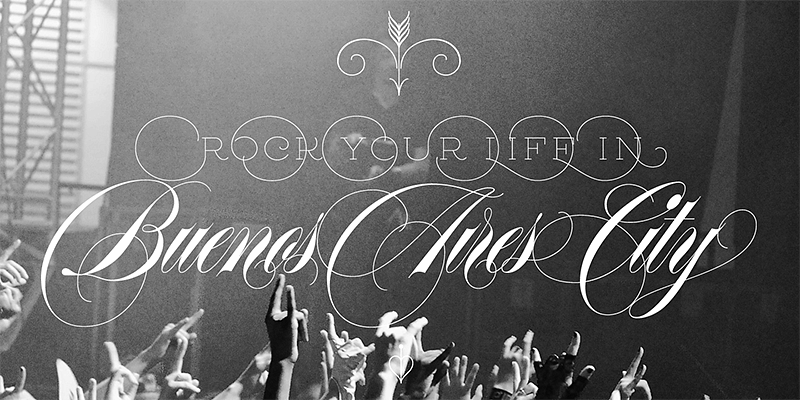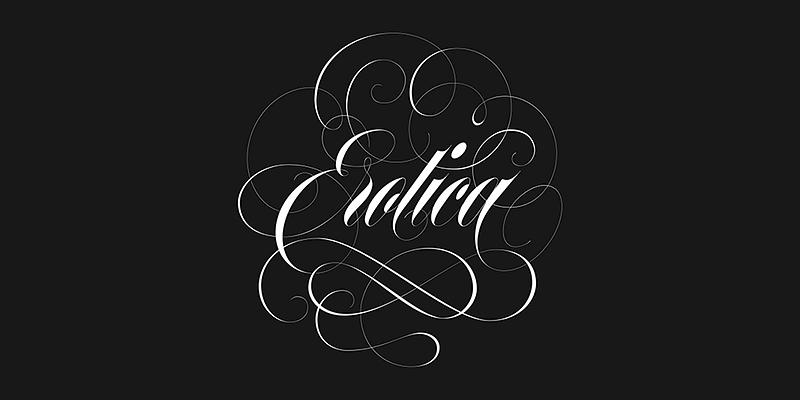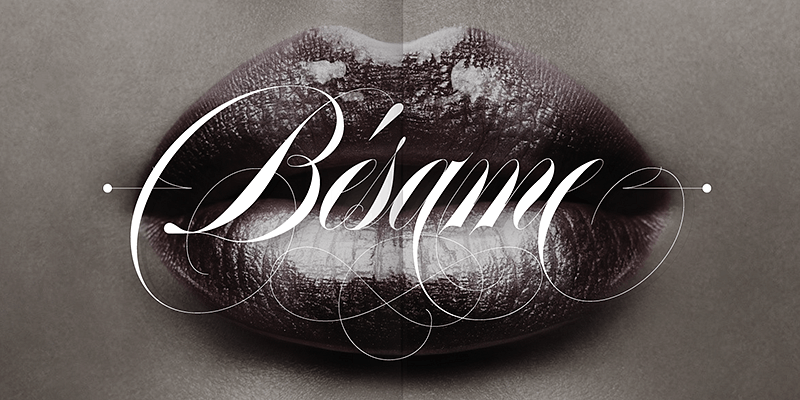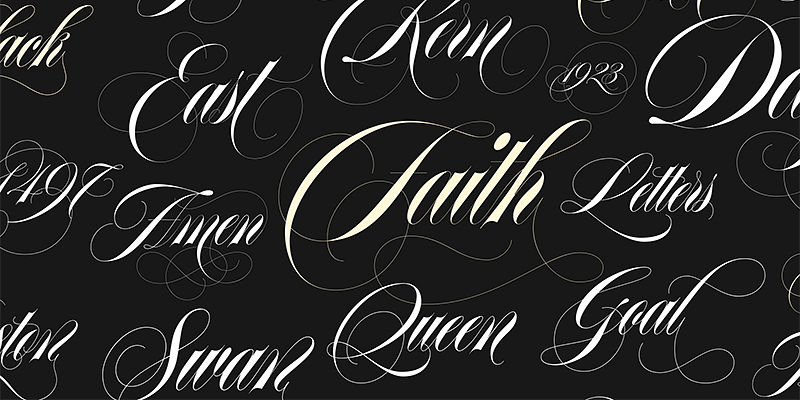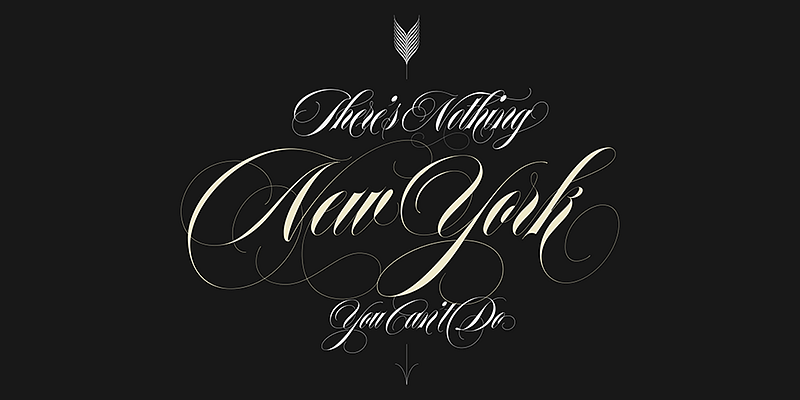
Sproviero Type hat einen preisgekrönten Katalog komplexer, schöner und moderner Schriften erstellt, bei dem kein Detail unberührt bleibt. Der Schriftgestalter Maximiliano Sproviero setzt seine Leidenschaft für Kalligraphie und Schrift in einer beeindruckenden Kollektion individueller Schriften um, die fantastisch dekoriert, fantasievoll geschwungen und atemberaubend originell sind. Ganz gleich um welches Produkt oder Medium es sich handelt, mit den Schriften von Sproviero Type schaffen Sie die Voraussetzungen dafür, dass Ihre Gedanken und Ideen in die Realität umgesetzt werden.